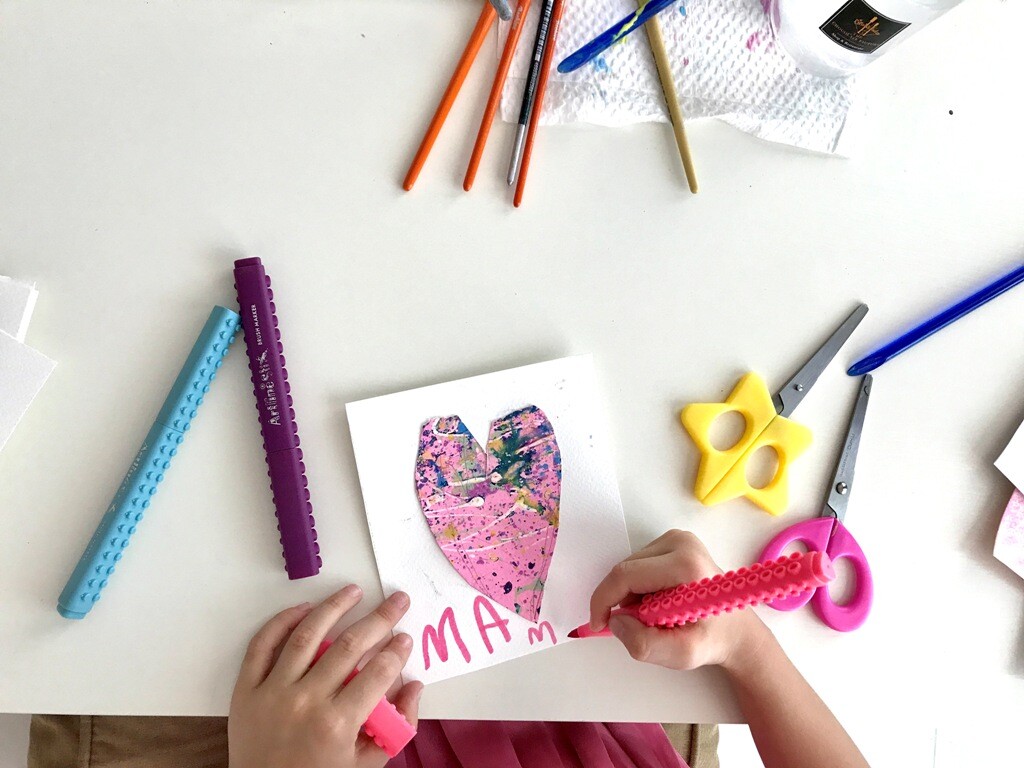
Для собственных писательских и учебных работ я купила Славяне чернильную ручку.
Сначала простенькую (недорогую), чтобы попробовать.
Затем, когда она к ней привыкла и загорелась идеей каллиграфии, пошли в магазин и выбрали более хорошую, но еще не Parker.⠀
Паркером пишу Я, с огромным удовольствием. Стильной, увесистой чернильной ручкой с толстым пером под серебро. И у нас есть правило, что каждый пишет своей ручкой и без спроса не берет чужую. Маминой ручкой писать не разрешено.
И для Славяны эта ручка - мечта!
И желание! И оно осуществится, как только мастерство ее вырастет. Это один из мотивационных моментов.
Со временем я стала вводить различные игры, которые помогали младшей изучать буквы, а старшей различать печатные и прописные, стилизованные, авторские.
Однажды Славяна пришла с радостным открытием: «Мама, весь мир состоит из букв!»
Это тот момент, которого я ждала!
Ведь с него начинается осознание и понимание необходимости письма. И обучение искусству красиво писать (каллиграфия) приобретает реальный смысл. Только вот мое видение изменилось тоже.
Первоначальная цель - "красиво писать", то есть "иметь красивый почерк" стала мелкой и не важной, на фоне всех возможностей, которые я увидела и в последствии показала девочкам.
Одна из них - профессия каллиграфа, дизайнера, художника. Ведь лично для себя я хотела овладеть этой темой не для почерка, а для создания собственных домашних и рабочих проектов: оформление альбомов для детей,подписи фотографий, табличек, картин на стены, а может и стен.
И эта та самая связь с жизнью. Когда изучаемый предмет не просто теория, а навык, применимый в жизни.
Так, каллиграфия стала отдельным занятием в нашем учебном дне. И достаточно регулярным. Появлялись различные интересные прописи (кириллица и латиница). И, о чудо! Славяна сама могла сесть с утра и исписать много листов подряд. Затем рассуждали, какие буквы сложные, какие простые. После пары недель таких комплексных занятий интерес закрепился и оставалось только продолжать создавать волшебство вокруг "мира букв". Что я и делала! И наблюдала.
Вот они - наши самые первые шедевры. Здесь пока еще не изучены основы написания букв, ритм и нажим на кисть. Все это впереди! Пока еще неуверенное владение кистью и тушью. Зато много заинтересованности.